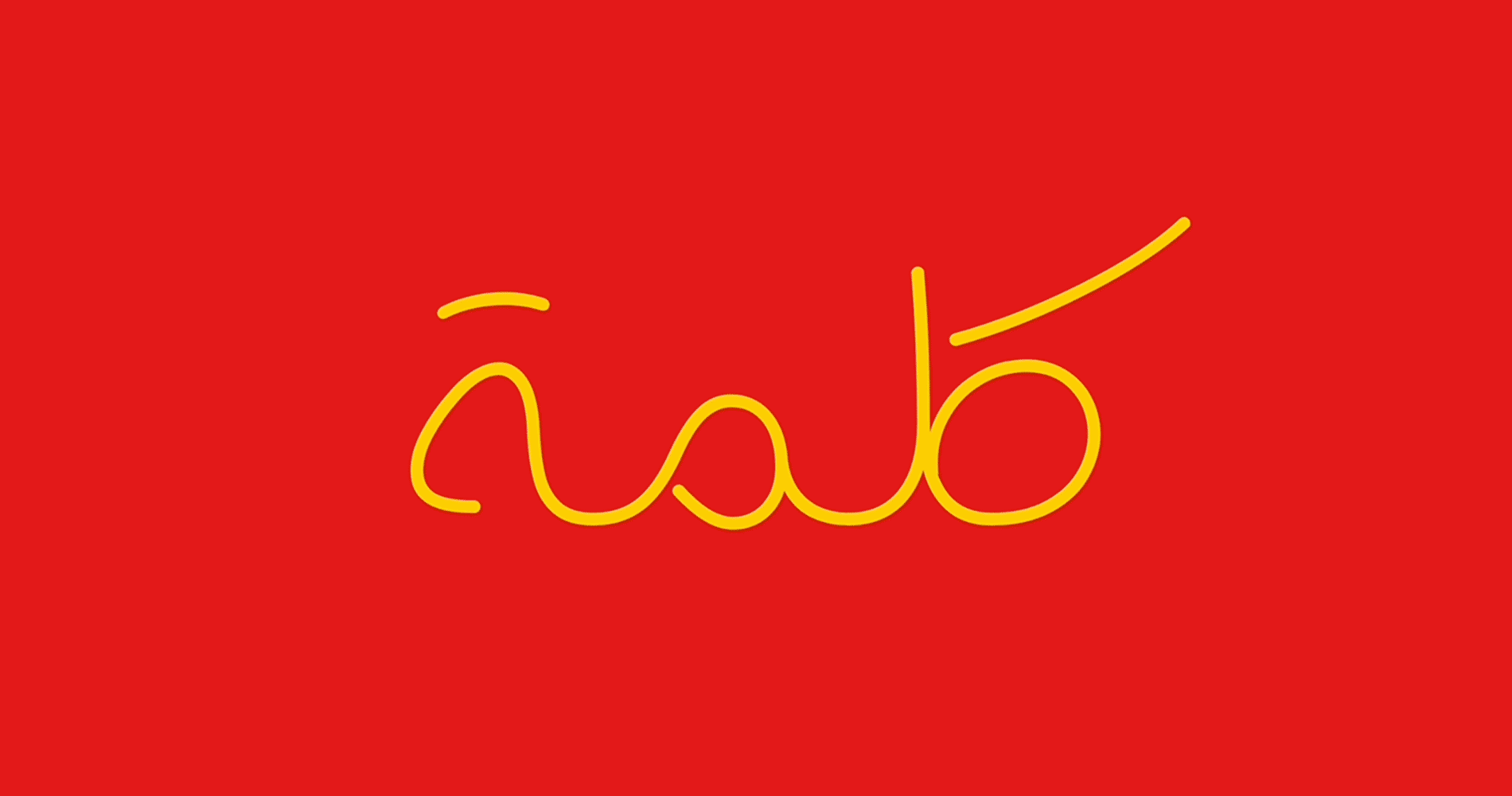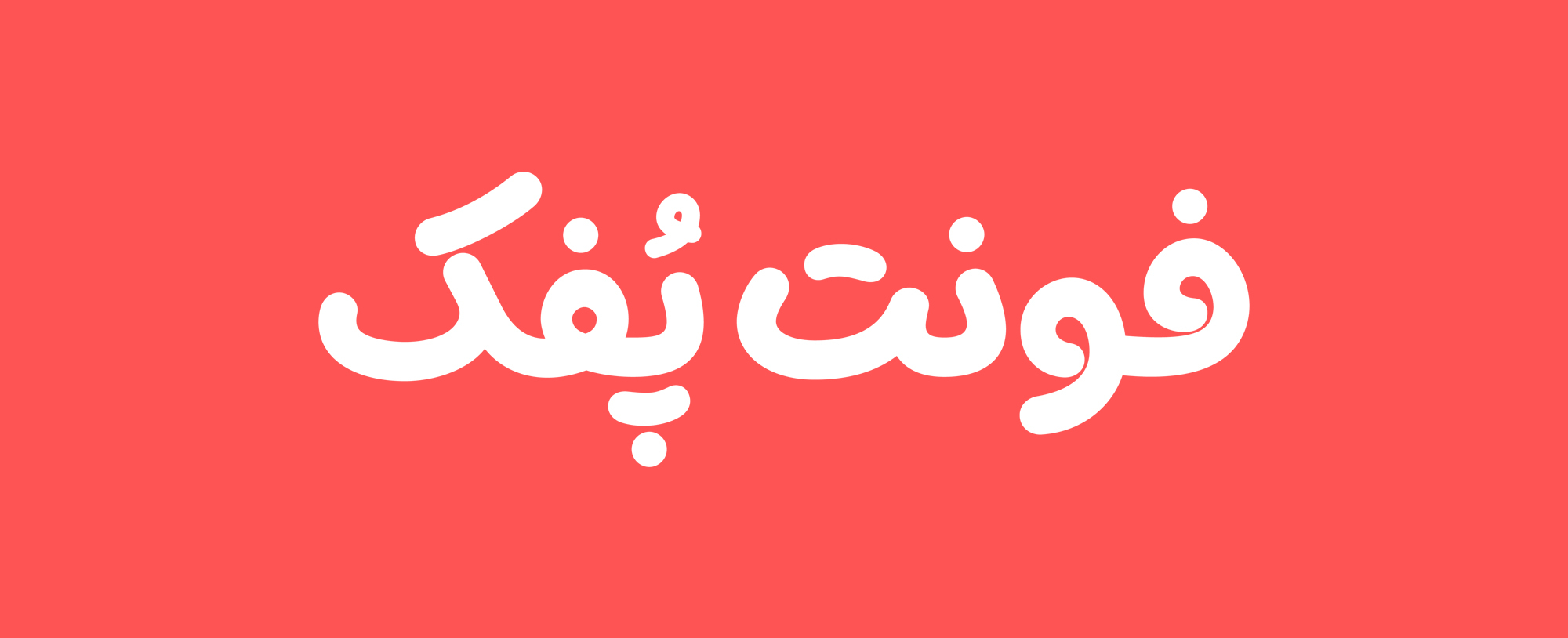
فونت پفک
پُفک یه فونت خوش‌خوراکه! خوراک هر چی که می‌خواید باحال و صمیمی به‌نظر برسه؛ از موضوعات مربوط به تفریح، جشن و بازی گرفته تا تبلیغات خوراکی‌ها و محتوای کودک و نوجوان.
پُفک شبیه فونت‌های دست‌نویسه اما بصورت بداهه طراحی نشده. این فونت بر خلاف ظاهر رها و راحتش خیلی حساب شده طراحی شده تا در اندازه‌های ریز هم خوانا باشه.
اگه دنبال راهی هستید که حرف‌های جدی رو با لحنی نرم و دوستانه بیان کنید، و خوانایی هم براتون مهمه، فونت پُفک بهترین انتخابه.
:: ۹ وزن متنوع از سبک تا سنگین
وزن‌های پایین برای متن‌های ریز و طولانی، وزن‌های بالاتر مناسب عنوان‌های تبلیغاتی.
:: مجموعه‌ای گسترده از حروف و ترکیبات جایگزین
بیشتر جایگزین‌ها به‌صورت خودکار فعّال هستن. بخشی هم از طریق تنظیمات OpenType قابل کنترلند.
به کمک این جایگزین‌ها می‌تونید:
اعداد انگلیسی رو فارسی کنید، تراز عمودی‌شون رو وسط چین کنید یا در لیست‌ها، اعداد هم‌عرض داشته باشید. همچنین می‌تونید شکل حروفی مثل «و»، «س‌ش»، «ههه»، «ح‌خ‌ج‌چ»، «ک‌گ»، «ی»، و «دندانه‌ها» رو تغییر بدید.
9 وزن